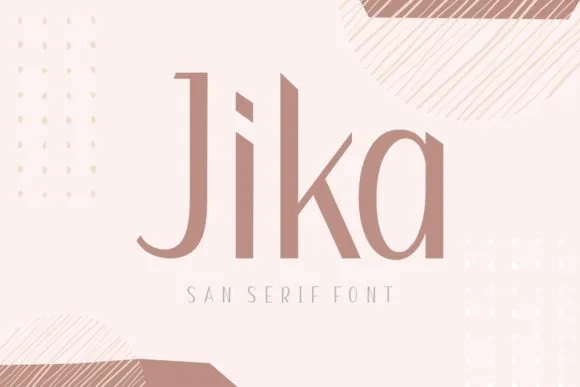
Jika Font
A Jika Font é uma elegante tipografia sans serif criada para oferecer um estilo minimalista e sofisticado que se adequa perfeitamente para projetos de branding. Esta fonte, com suas bordas suaves, transmite um toque autêntico de trabalho à mão tradicional. Ideal tanto para empresas quanto para designers a procura por uma tipografia moderna e minimalista, a Jika captura a essência contemporânea sem perder o aspecto elegante que torna as fontes serifadas tão populares. Suas linhas leves e perfeitas combinam-se perfeitamente com a simplicidade do design moderno, oferecendo uma combinação de facilidade de leitura e estilo distintivo. É perfeito para criar mensagens claramente visíveis sem perder o charme de um design simplesmente genial.